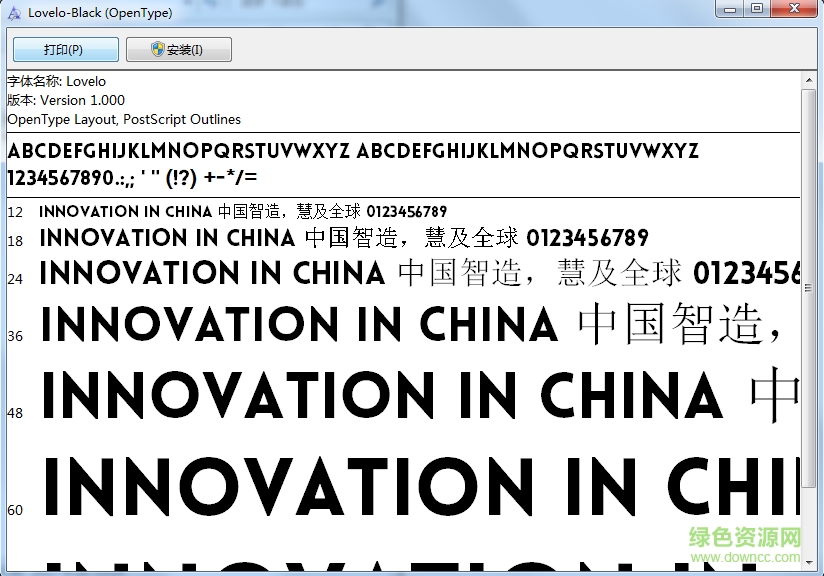
lovelo black是一款加粗加黑的實心英雄字體,簡約現(xiàn)代感的造型,讓你的英文書寫更具時代厚重感,喜歡的朋友歡迎來綠色資源網(wǎng)免費下載!
lovelo字體介紹
lovelo是一款藝術(shù)字體,也叫做lovelo black,字跡流暢造型簡單,使用于廣告設(shè)計、海報印刷、名片設(shè)計等行業(yè)。